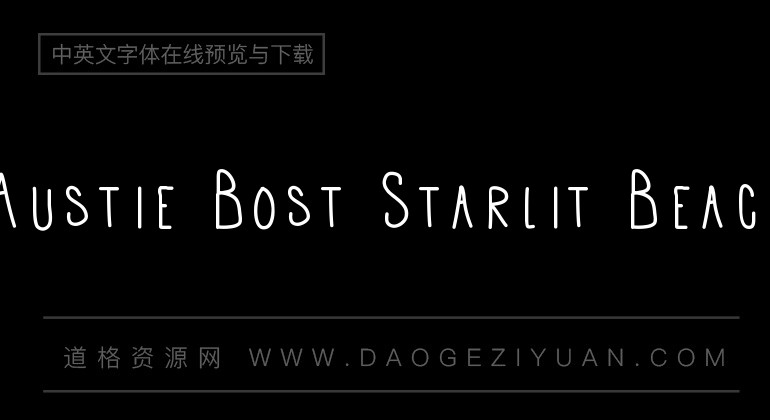
Austie Bost Starlit Beach 字体是由美国著名设计师 Austie Bost 创作的一款简洁明快的手写字体。它由细腻的笔触和流畅的线条组成,具有灵动的曲线,清晰的字形,非常适合用于卡片、海报、书籍封面、T恤和其他设计项目。它的特点是温柔而柔和的气氛,可以为设计师提供更多的想象空间,使设计的艺术性更加出彩。内容介绍
Austie Bost Starlit Beach是一款非常不错的手写艺术字体,具有很好的视觉感,适合于文化类的宣传设计、商业类品牌的广告和产品包装设计以及个性化文字排版等较多场景。